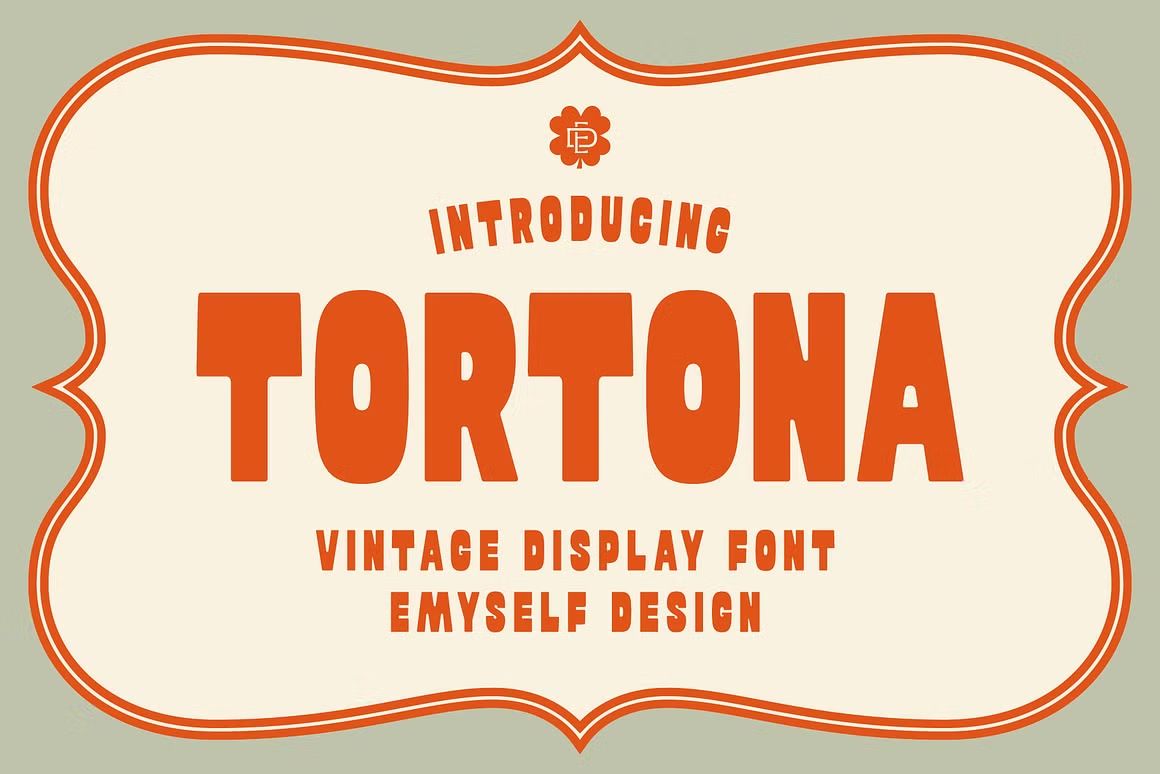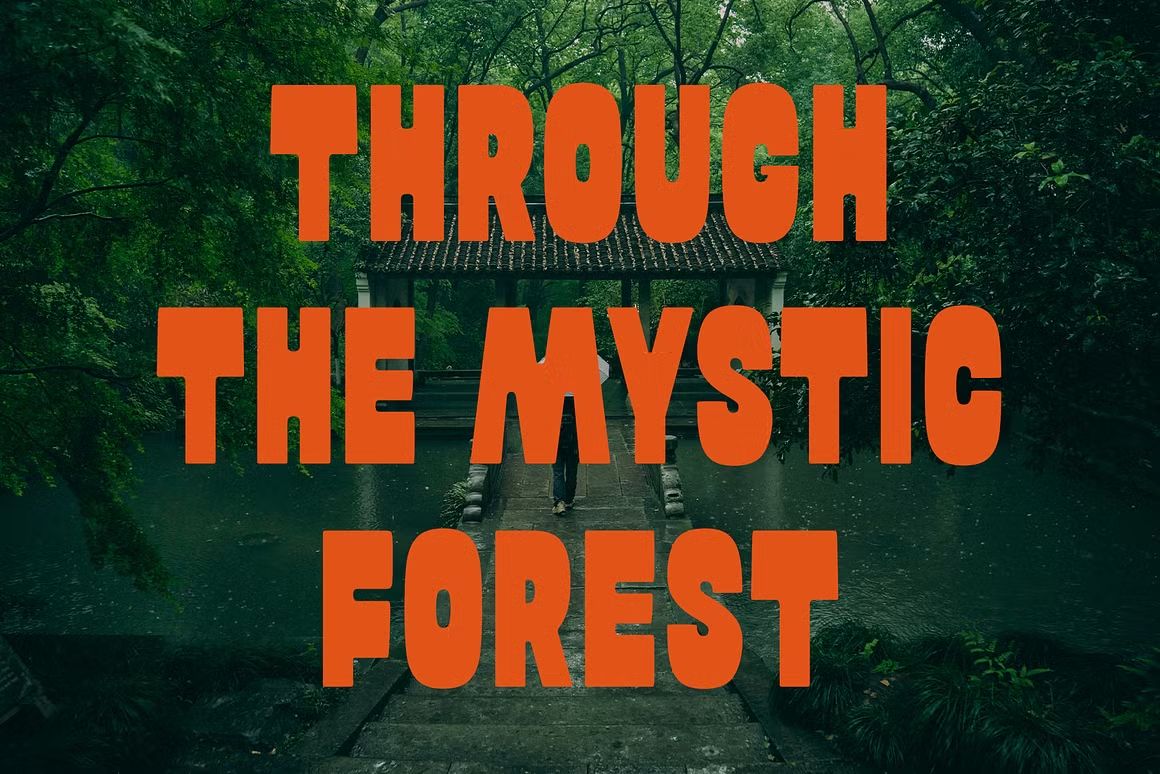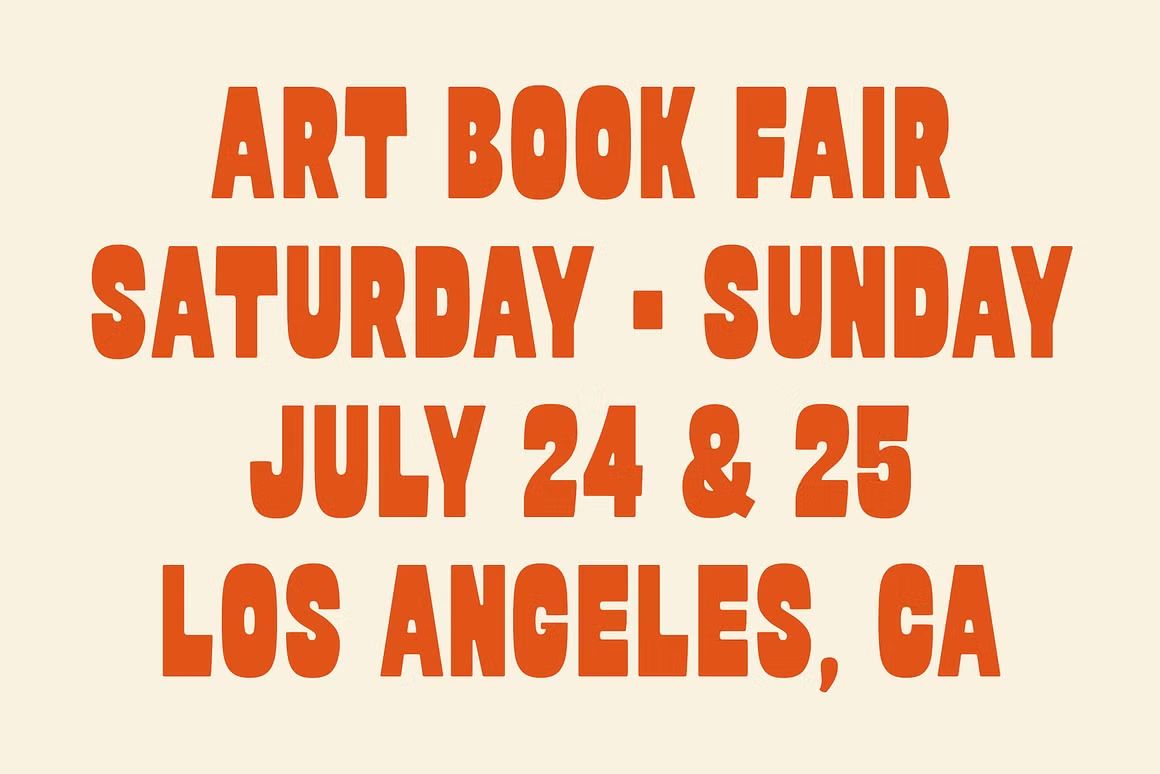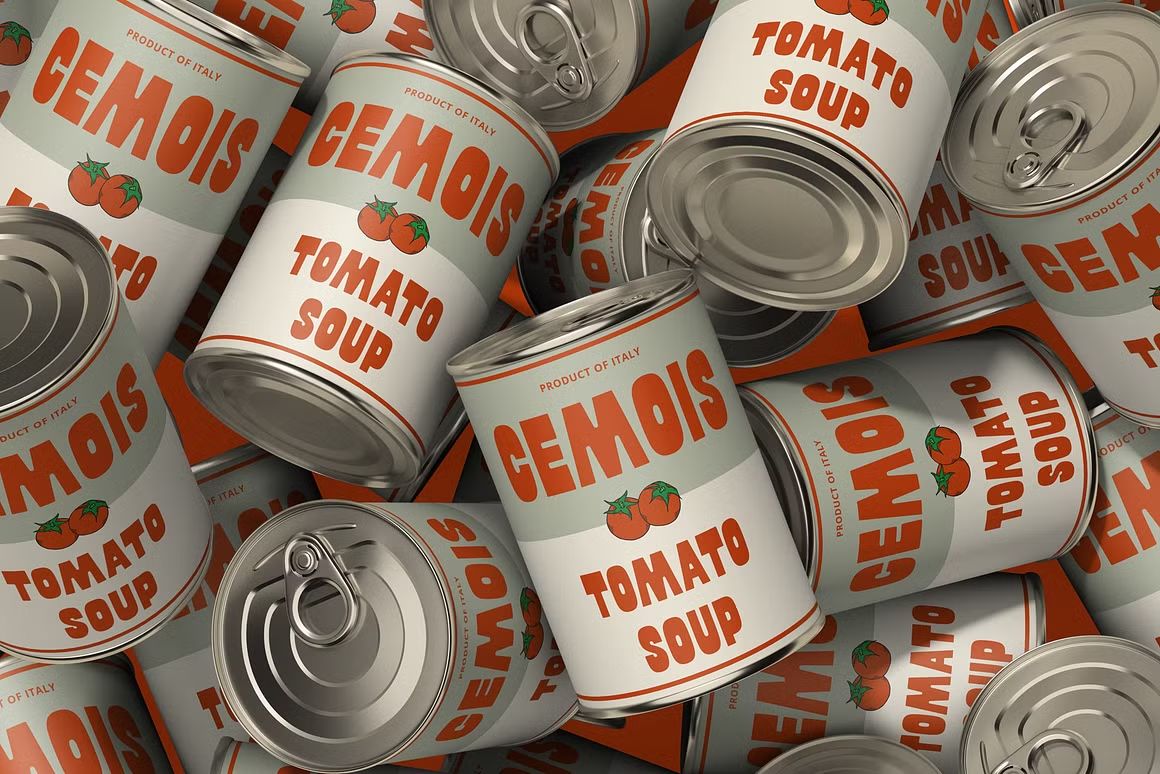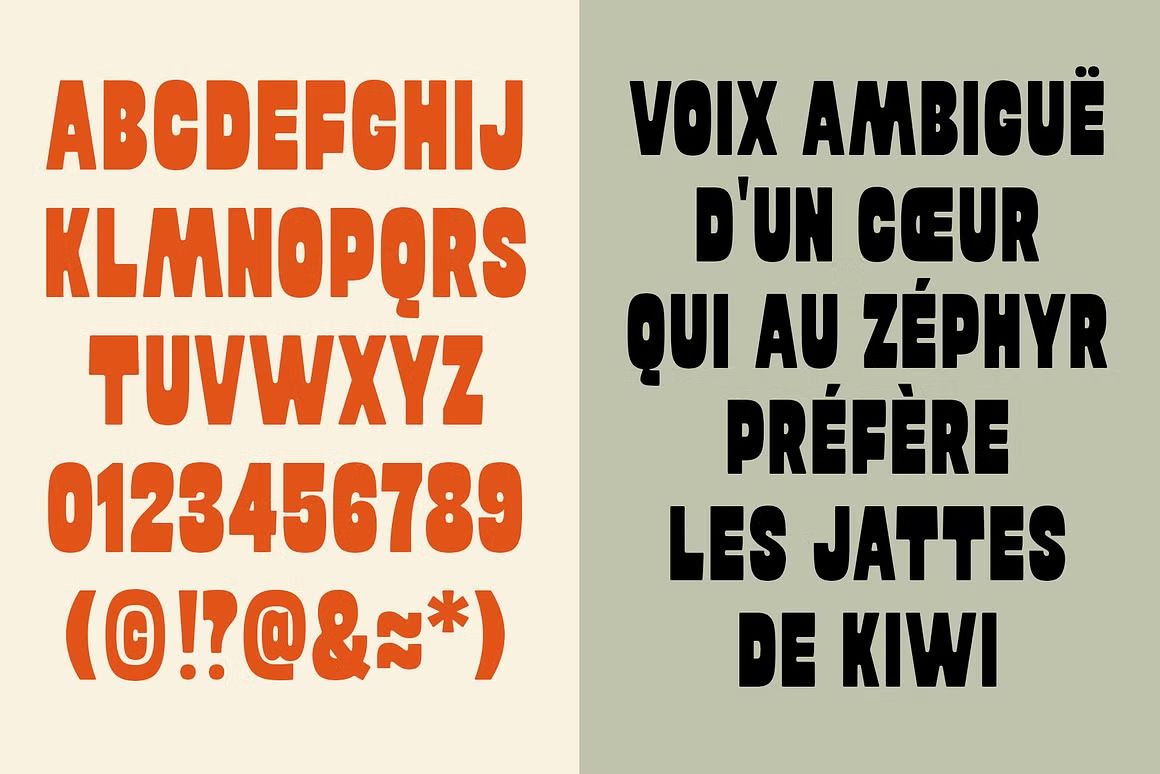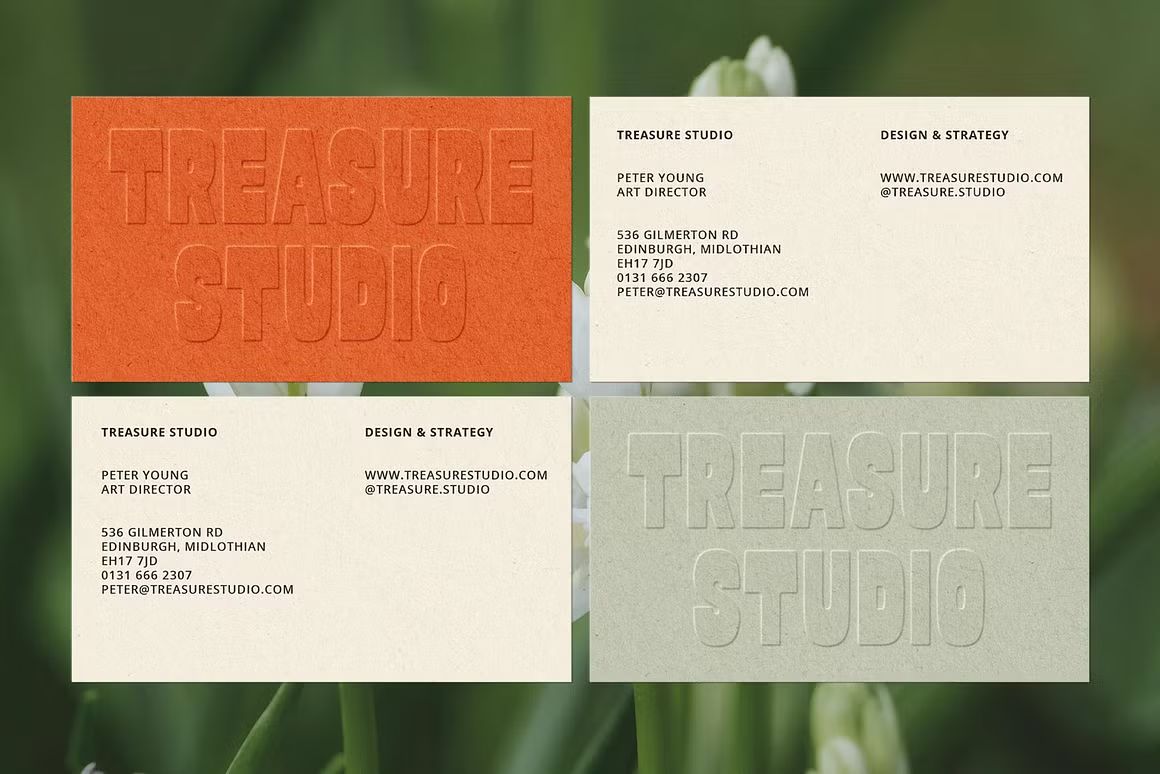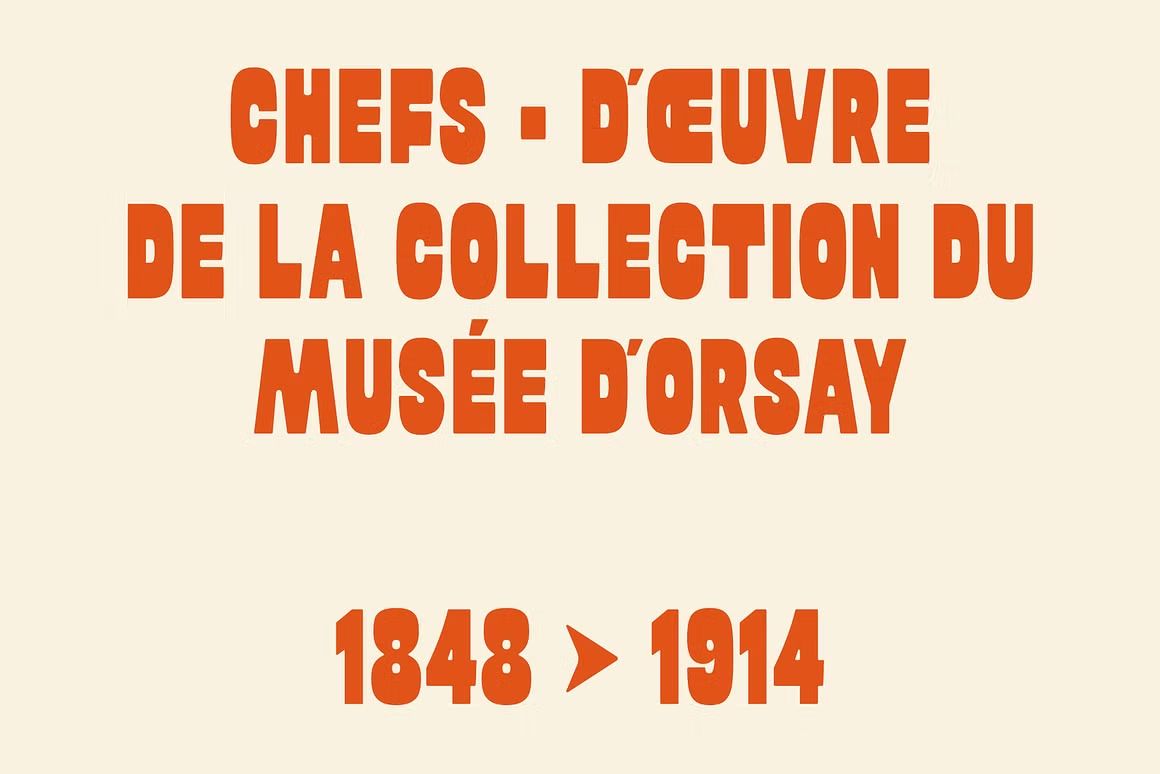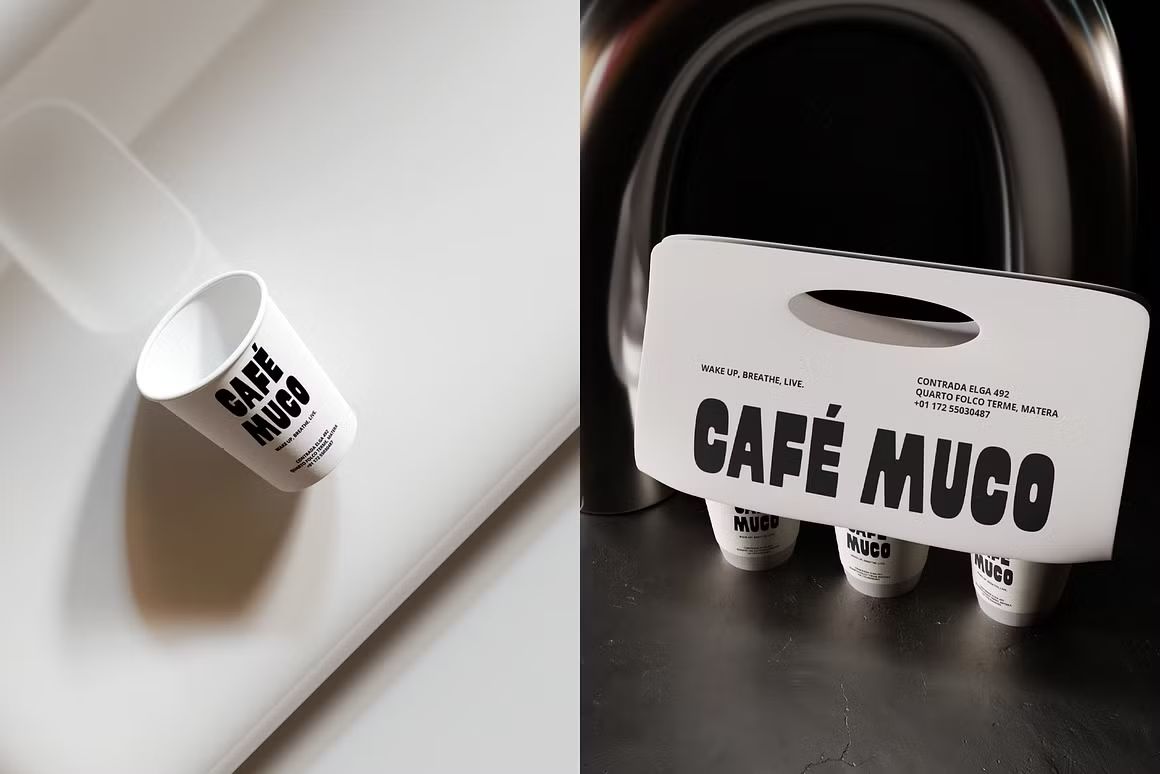
ED Tortona – Sans Serif Font
ED Tortona adalah font sans serif modern dengan karakter tegas, minimalis, dan elegan. Dirancang dengan proporsi geometris dan bentuk huruf yang bersih, font ini sangat cocok untuk branding, desain editorial, UI/UX, kemasan, serta presentasi profesional. ED Tortona menawarkan kesan profesional dan kontemporer yang cocok untuk berbagai kebutuhan visual.
• Sans serif geometris dengan tampilan bersih dan modern
• Ideal untuk branding, editorial, dan tampilan digital
• Termasuk huruf kapital, kecil, angka, dan simbol